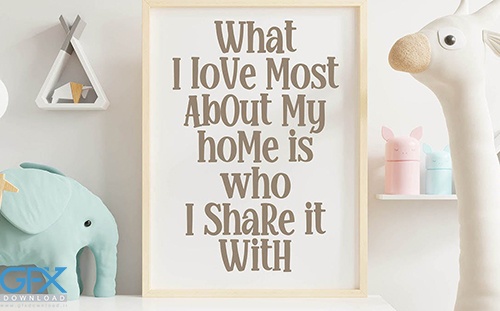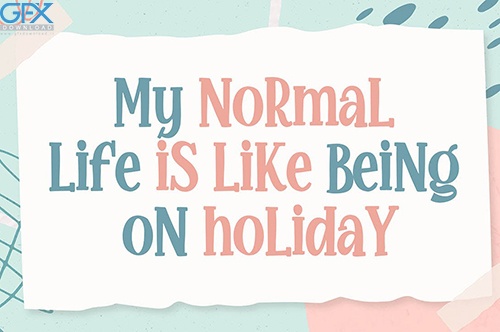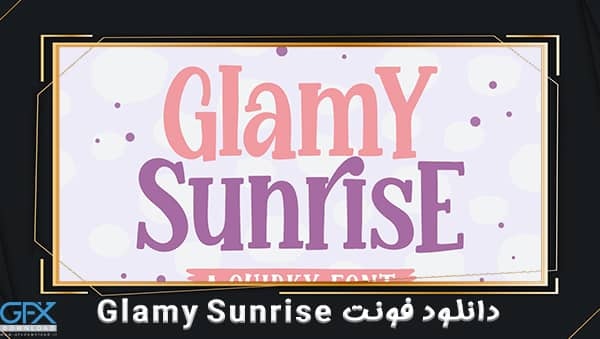
دانلود فونت Glamy Sunrise یکی از جدید ترین فونت ها . در این پست با معرفی محصول جدید ما نام Glamy Sunrise a Quirky Font با شما همراه هستیم. این فونت با الهام از سبک بازیگوش با تم سرگرم کننده بسیار مناسب برای پوستر ، بسته بندی ، طراحی تم بازی و غیره است. شامل حروف بزرگ، حروف کوچک، عدد ، نقطه گذاری، چند زبانه، رمزگذاری PUA، Opentype می باشد.